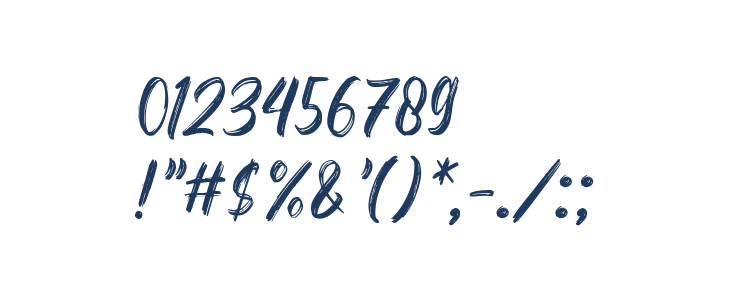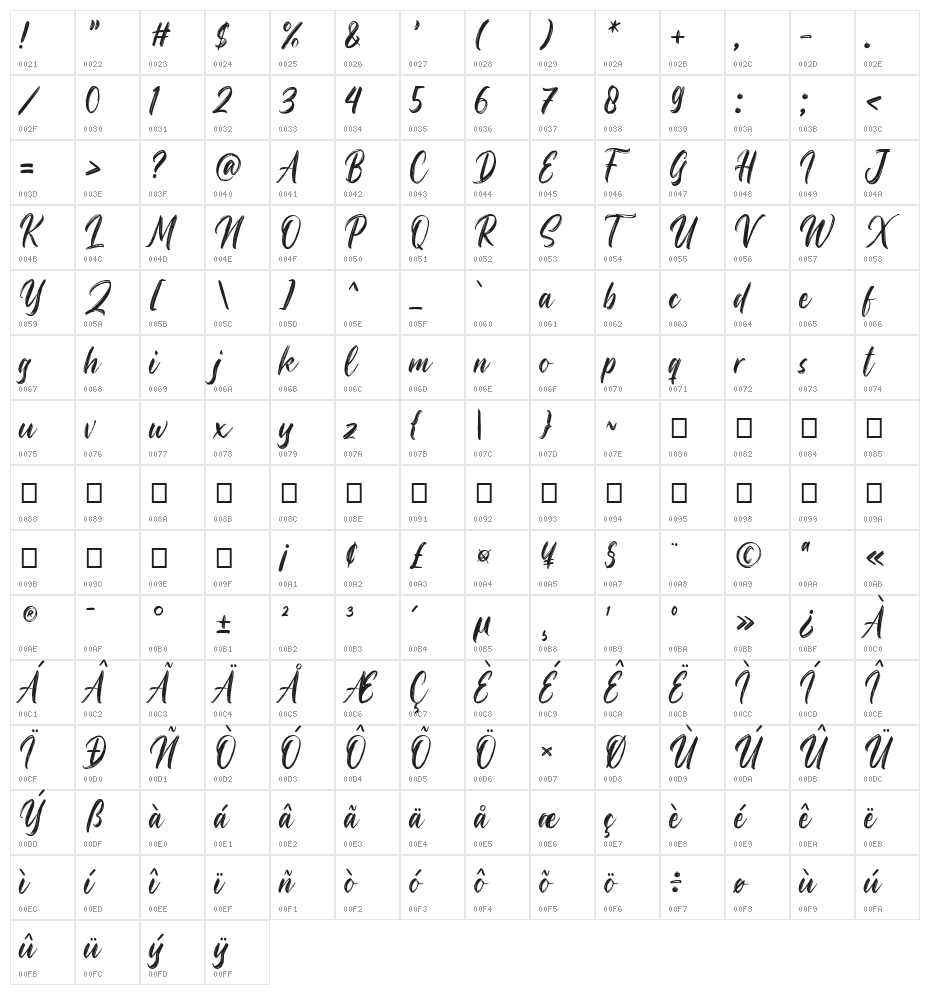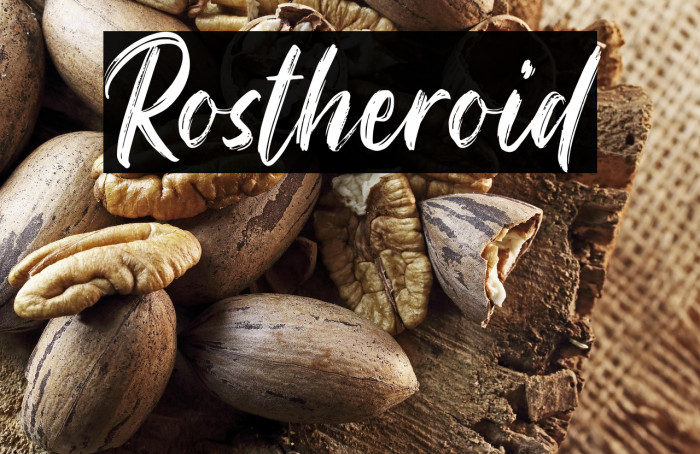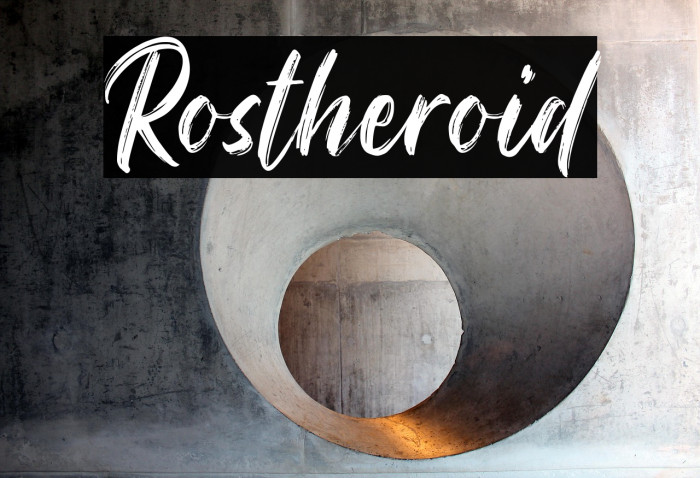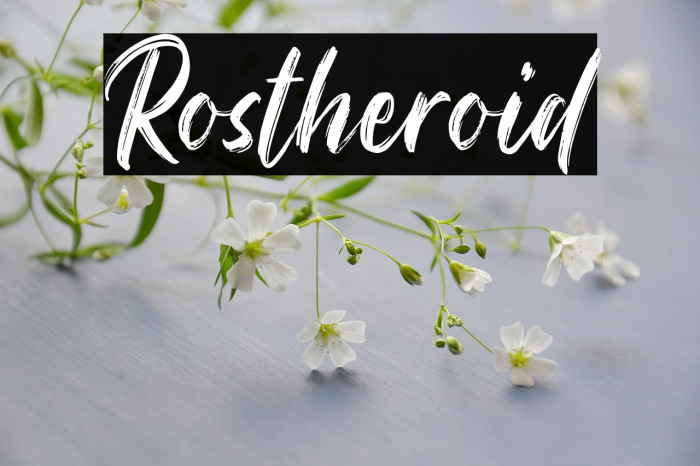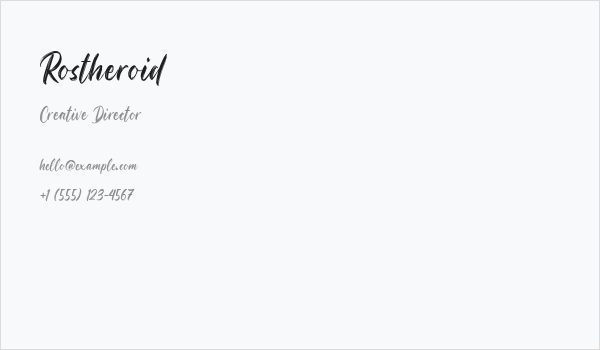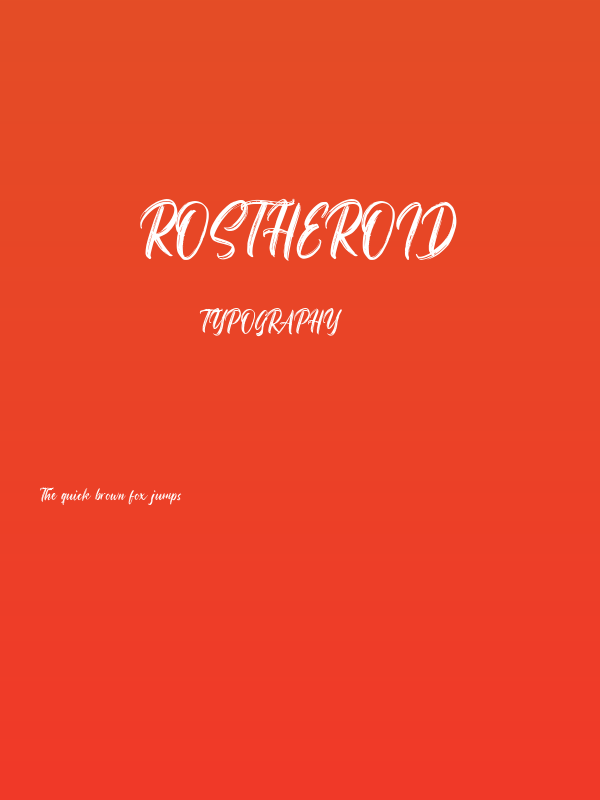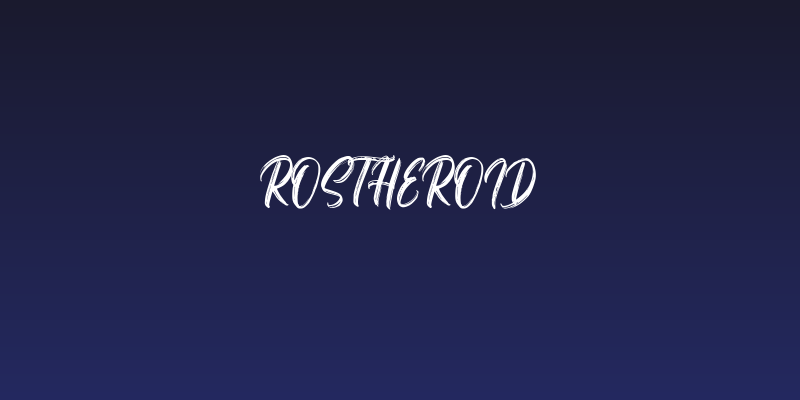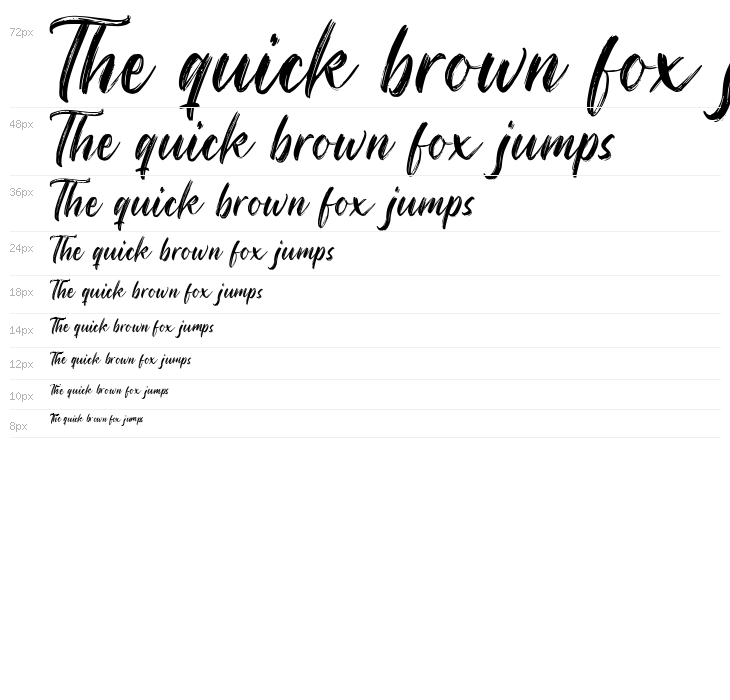
Rostheroid Font
| Caso de uso | Logos, Headlines, Posters |
| Proyectos propuestos | Ideal for branding, packaging, posters, and invitations where a personal and artistic touch is desired. |